フォントワークスは年間定額制フォントサービス「LETS」「モトヤLETS」にて新たに「LETS」に20書体、「モトヤLETS」に3書体の提供を8月22日から開始した。
<日本語書体>
・筑紫Q明朝L-L[Std]
・筑紫Q明朝S-L [Std]
・UD丸ゴ_ラージ-E/H/U [Pr6 / Pr6N]
・UD丸ゴ_スモール-E/H/U [Pr6 / Pr6N]
<多言語書体>
・FWアラビア-R/DB/B
・FWヒンディ-R/DB/B
・モトヤアラタ 2B/4/6 [Std]
「LETS」には、筑紫書体シリーズとして「筑紫Q明朝」のラージとスモール、「UDフォント」シリーズの丸ゴシック体「UD丸ゴ_ラージ」「UD丸ゴ_スモール」のE/H/U、そして多言語フォントとしてアラビア語とヒンディ御の各3ウエイトが加わった。
「筑紫Q明朝」は、キュッと絞った小さなフトコロとそこから伸びる長い手足のようなハライが特徴的な漢字と手書き風の「かな」が、横組みでは筆記体のような一体感とリズムを、縦組みでは日本語固有の縦書きのリズムを奏でる書体になっている。
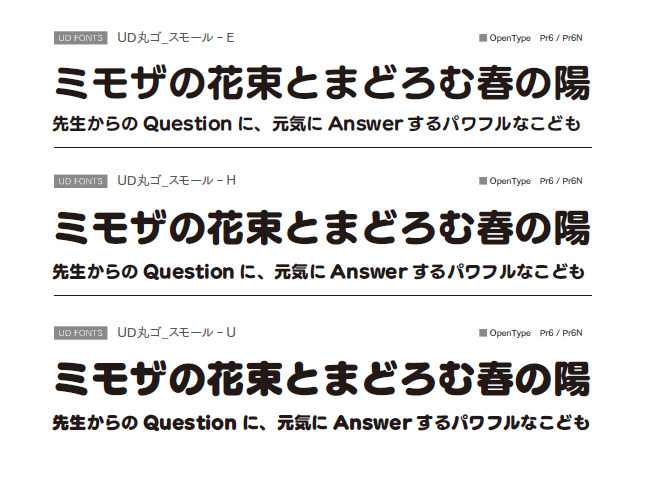
「UD丸ゴ_ラージ」「UD丸ゴ_スモール」は、「UD角ゴ」同様に太いウエイトの拡張が展開された。
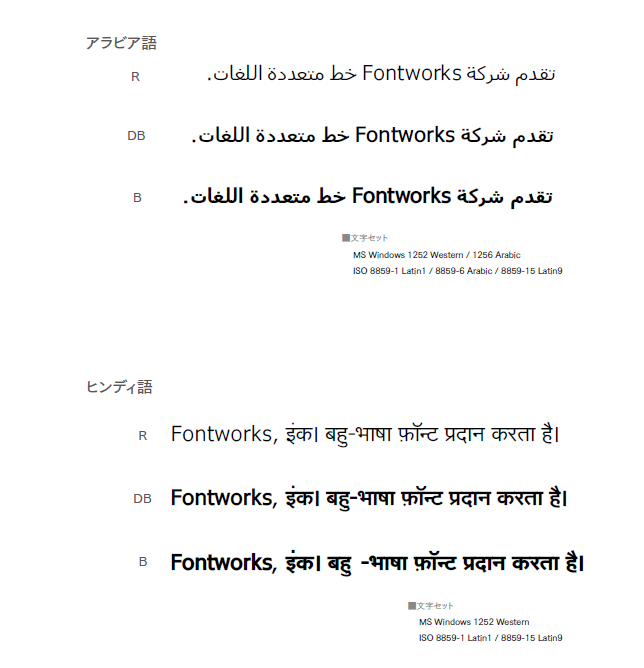
また多言語フォントでは、フォントワークス「UD角ゴ」と組み合わせての使用が推奨されるアラビア語フォントとヒンディ語フォントを提供された。
仮名フォント「Mkアラタ」のレトロな雰囲気はそのままに「Mkアラタ」が持つエレメントの特徴を持った漢字を収録し、さらに仮名をリデザインした新たな「アラタ」書体、3ウエイトが提供となった。
筑紫書体シリーズとして「筑紫Q明朝」のラージとスモール、「UDフォント」シリーズに丸ゴシック体「UD丸ゴ_ラージ」「UD丸ゴ_スモール」のE/H/U、そして多言語フォントとしてアラビアとヒンディの各3ウエイトが加わります。
今回新書体として登場した、「筑紫Q明朝」は、キュッと絞った小さなフトコロとそこから伸びる長い手足のようなハライが特徴的な漢字と手書き風の「かな」が、横組みではあたかも筆記体のような一体感とリズムを、縦組みでは日本語固有の縦書きのリズムを奏でる書体です。
「UD丸ゴ_ラージ」「UD丸ゴ_スモール」は、「UD角ゴ」同様、会員さまより多くのご要望をいただいた太いウエイトの拡張を、また、多言語フォントより、フォントワークスの「UD角ゴ」と組み合わせての使用がオススメな、アラビア語フォントとヒンディ語フォントをご提供します。
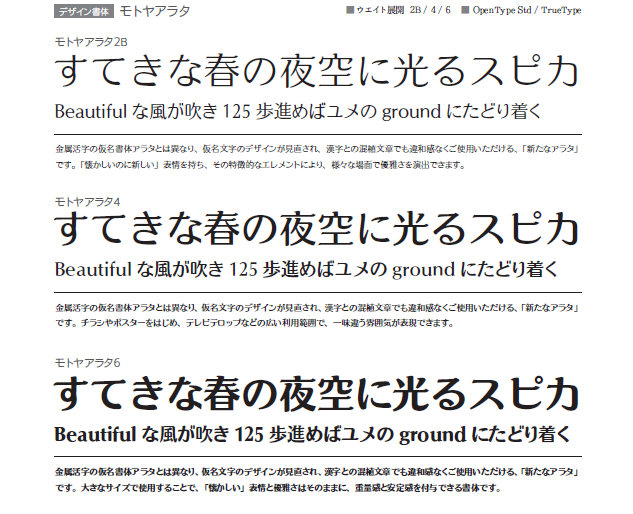
仮名フォント「Mkアラタ」のレトロな雰囲気はそのままに「Mkアラタ」が持つエレメントの特徴を持った漢字を収録し、さらに仮名をリデザインした新たな「アラタ」書体、3ウエイトが提供となった。